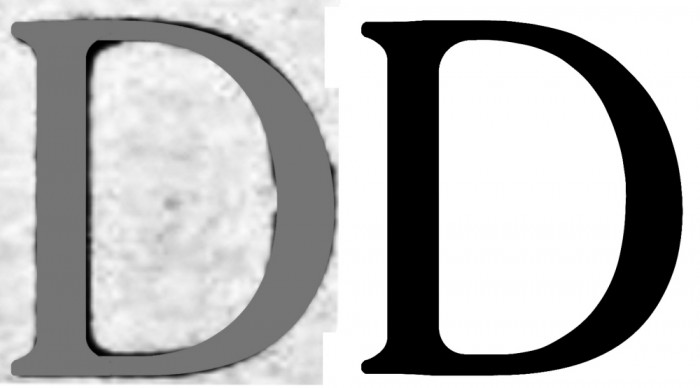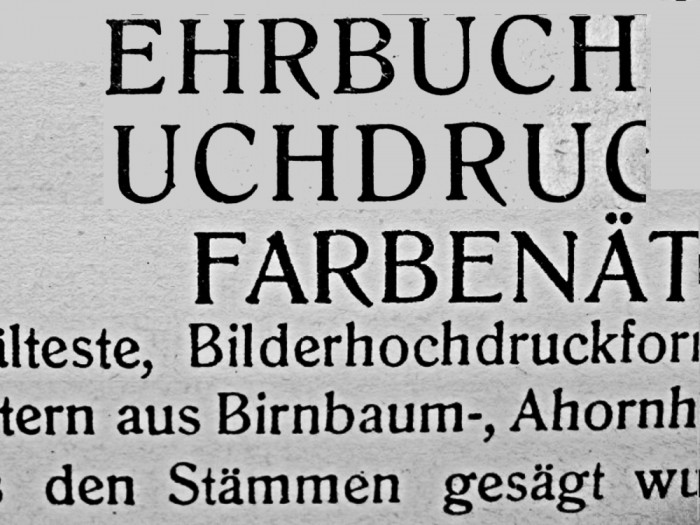
Romanische Antiqua - Hilfe!
Hallo, arbeite ich an die Gewinnung des "Romanische Antiqua" Schriftart für True Type Format. Ich bin aus Argentinien und ich bin sehr Interesse an Stummfilme, besonders die, die in meinem Land gemacht. Mehrere Filme verwendet die Romanische  Antiqua (oder Pfeil Antiqua) in den Zwischentiteln. I jemand Texte whith dieser Schriftart, werde ich einige Scans zu schätzen wissen. Speziell von einigen Hauptstädten, wie J, M, Q, SVWXY Z. Hier ist ein Beispiel:
Diese Bilder wurden von einem deutschen Benutzer, die dann nicht encotrar könnte veröffentlicht. Ich entschuldige mich dafür.
Eine eine Probe meiner Arbeit (mit Font Creator):
Martin Z. Schröder has some samples of it on his blog (I think):
The samples are obviously from the book »Lehrbuch für Buchdrucker« by Arthur W. Unger, Vienna, 1922, Verlag der Hölder-Pichler-Tempsky A.G.
Maybe Mr. Schröder can tell more, if he is looking in here, as he is a member of this forum.